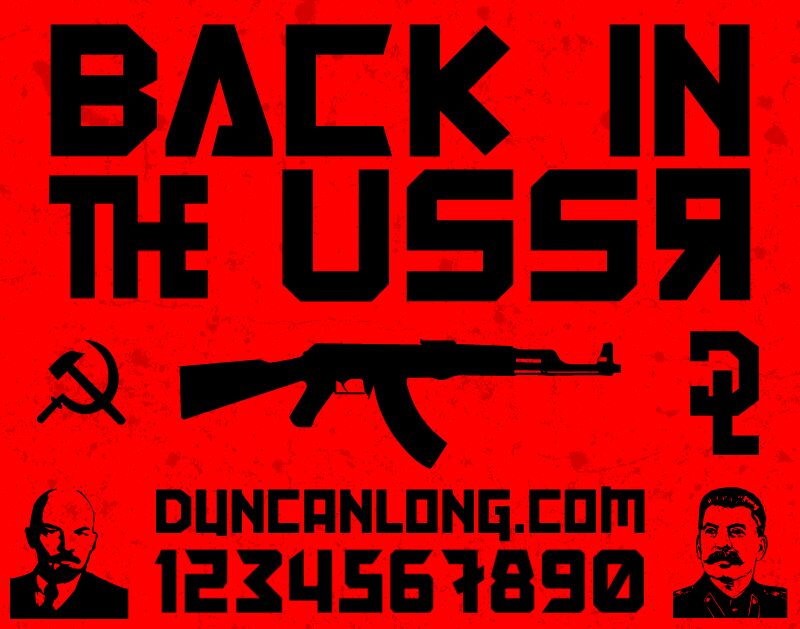
Back In The USSR DL von Duncan Long ist eine kostenlose, eckige Techno-Großbuchstaben-Display-Schrift mit einem strengen, retrofuturistischen Charakter. Breite geometrische Striche, quadratische Öffnungen und scharf geschnittene Ecken verleihen den Buchstaben die Wucht konstruierter Beschilderungen, während eine enge Laufweite das gesamte Schriftbild kompakt und durchsetzungsstark hält.
Ihr blockhafter Rhythmus sorgt für eine prägnante visuelle Präsenz bei Plakatkampagnen und Spieletiteln. Verwenden Sie diese kostenlose Schrift für elektronische Albumcover, Event-Grafiken, Sci-Fi-Verpackungen oder Textildrucke, wo ihre industrielle Geometrie Bilder erden und Themen wie Maschinerie, Technologie und alternative Zukunftsszenarien untermauern kann.
Enthält einige Extras.